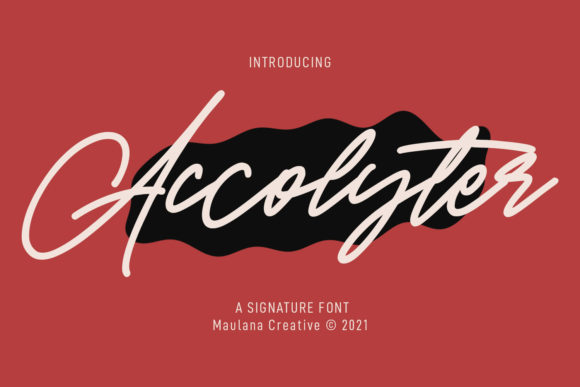
Название: Accolyter Font (2021)
Accolyter - это стильный и спокойный рукописный шрифт.
Этот нежный шрифт будет великолепно смотреться на различных дизайнерских идеях.
Он добавит радостный и романтичный штрих в каждый ваш проект!
Название: Accolyter Font (2021)
Accolyter - это стильный и спокойный рукописный шрифт.
Этот нежный шрифт будет великолепно смотреться на различных дизайнерских идеях.
Он добавит радостный и романтичный штрих в каждый ваш проект!